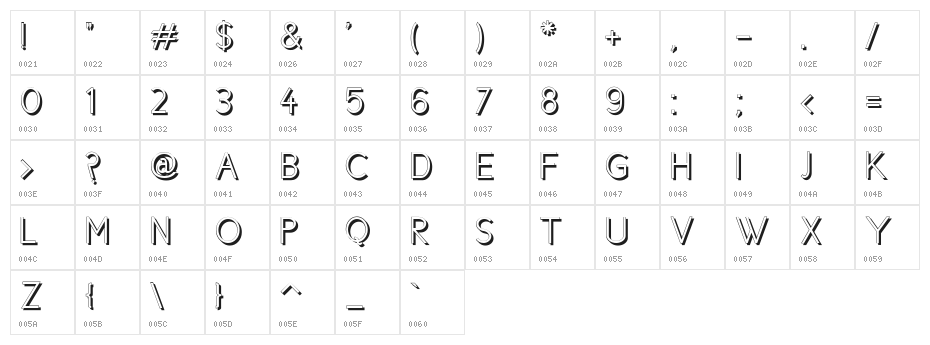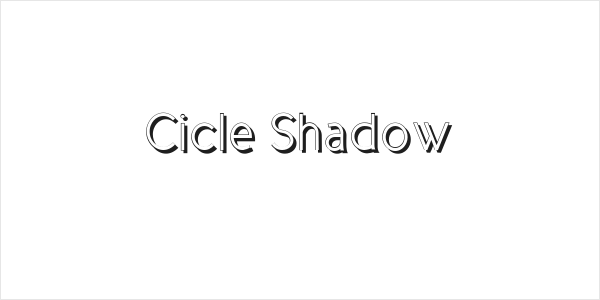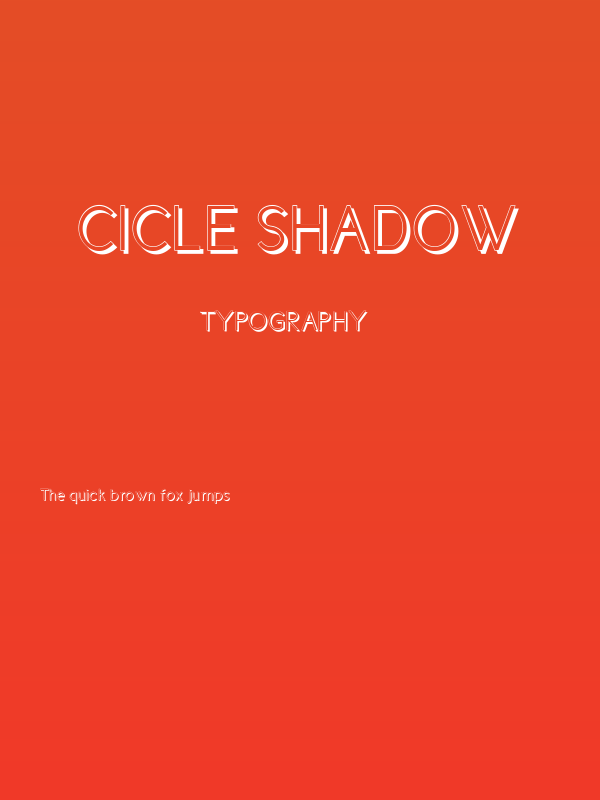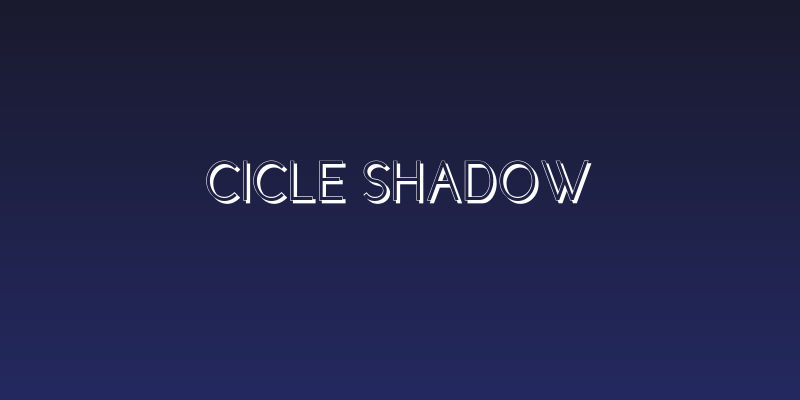
Cicle Shadow Font
✎ Sans Serif
| Vorgeschlagene Projekte | Ideal for branding, posters, headlines, and digital media where a modern and dynamic look is desired. |